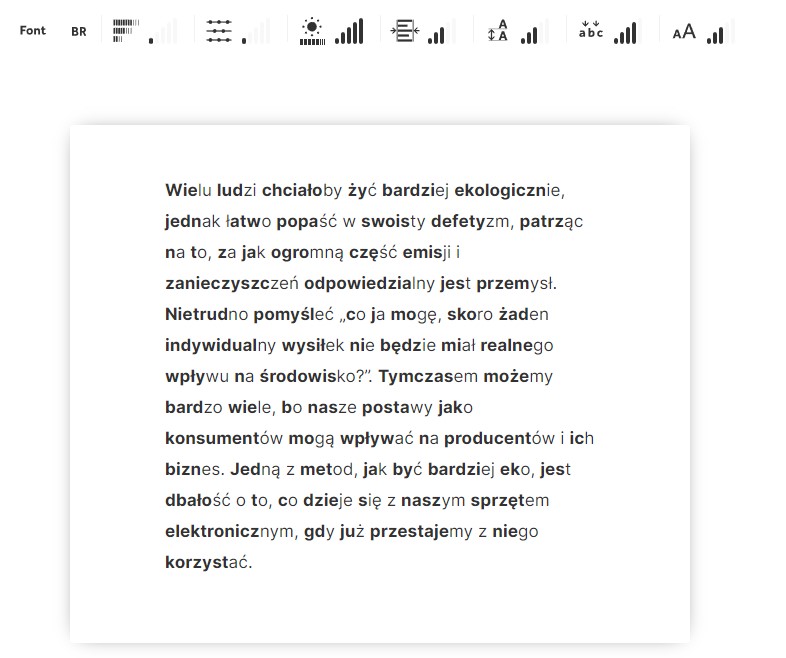
Pomoże ci czytać i zwiększy koncentrację. Cud? Nie, to czcionka bioniczna
Jeżeli kiedykolwiek miałeś problemy z koncentracją podczas czytania lub po prostu chciałeś je przyspieszyć, szwajcarzy mają pomysł na to jak ci pomóc. Kurs? Mikroczip wszczepiany do mózgu? A może wspomaganie sztuczną inteligencją? Nie, odpowiedzią jest... czcionka.
Bonic Reading. Bioniczna czcionka pomaga czytać
Czytanie i pisanie są podstawowymi czynnościami wymaganymi do nauki, stanowiącymi pierwszy krok w edukacji każdego dziecka. Na lekcjach historii dział starożytności otwierany jest stwierdzeniem, że to właśnie pismo i jego odczyt doprowadziły do powstania pierwszych państw, a spora część wieku XX upłynęła pod znakiem sukcesywnej redukcji problemu analfabetyzmu.
Szwajcarska bioniczna czcionka pomaga czytać i podbija Internet
Analfabetyzm w swoim podstawowym znaczeniu praktycznie nie występuje w rozwiniętych państwach. Jednakże nie oznacza to, że każdy z nas czyta równie płynnie. Jedni czytają szybciej, inni wolniej. Urządzenie, na którym czytamy (ekran telefonu czy czytnik ebooków) lub format wydruku (książka lub gazeta) oraz niektóre schorzenia psychiatryczne i neurologiczne również wpływają na nie tylko prędkość czytania, ale i koncentrację, a to przekłada się na nie tylko to ile tekstu przeczytaliśmy, ale też ile z niego zrozumieliśmy.
Bionic Reading pogrubia i zwiększenia rozmiary pierwszych liter w wyrazie
Istnieje jeszcze jeden czynnik: krój pisma. Jego rozmiar, styl, odstęp między znakami oraz efekty mu towarzyszące również mają ogromny wpływ na to jak szybko czytasz i w efekcie, ile rozumiesz z tego co czytasz. Wie to także szwajcarski projektant Renato Casutt, który zaprojektował Bionic Reading, unikalny krój pisma, który za pomocą pogrubienia i zwiększenia rozmiary pierwszych liter w wyrazie przyspiesza czytanie.
"Bionic Reading ma na celu pomóc w przyswajaniu tekstu. Postrzegamy postęp technologiczny jako szansę dla wszystkich, którzy chcą zwiększyć przyjemność z czytania - w skupiony sposób, bez rozpraszania uwagi - w tym hałaśliwym i pełnym pośpiechu świecie" - pisze Casutt na stronie projektu
Bionic Reading oprócz konwersji tekstu na bardziej przystępny krój pisma oferuje także jego modyfikację - rozszerzenie pola tekstowego, zmniejszenie lub zwiększenie ilości pogrubionych liter, zwiększenie rozmiaru tekstu oraz posiada inne funkcje zwiększające dostępność. Ponadto obsługuje polskie znaki diakrytyczne.